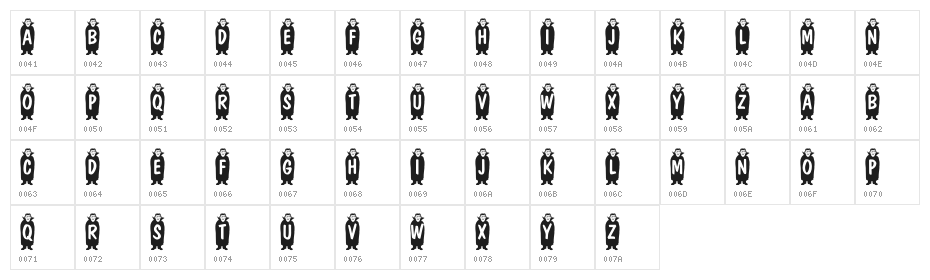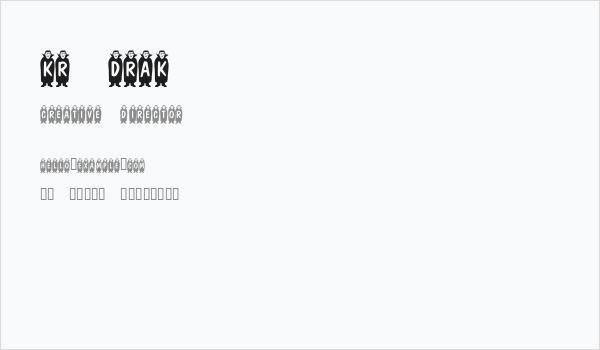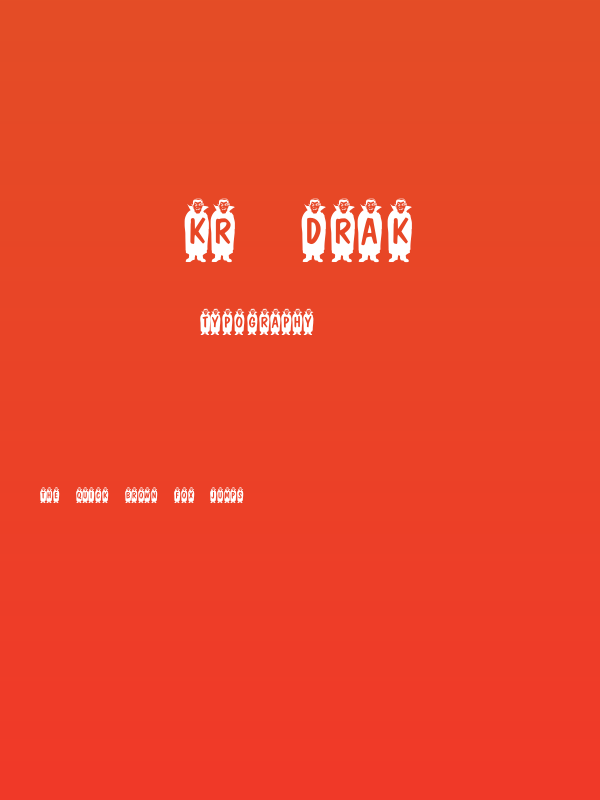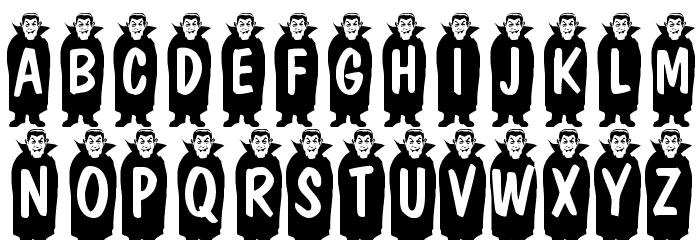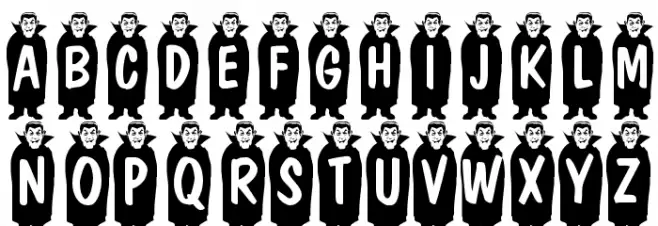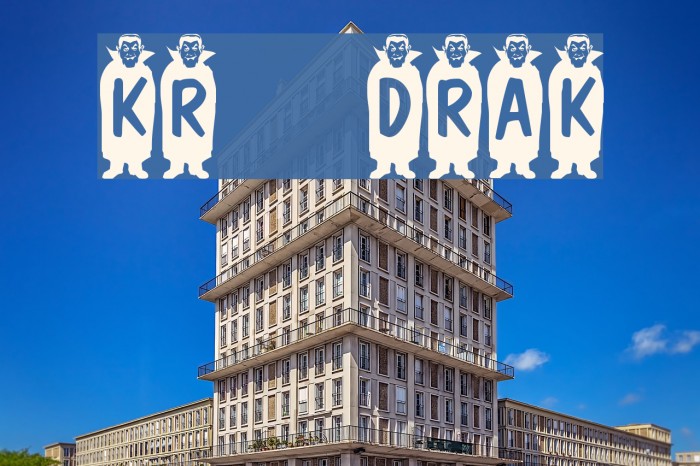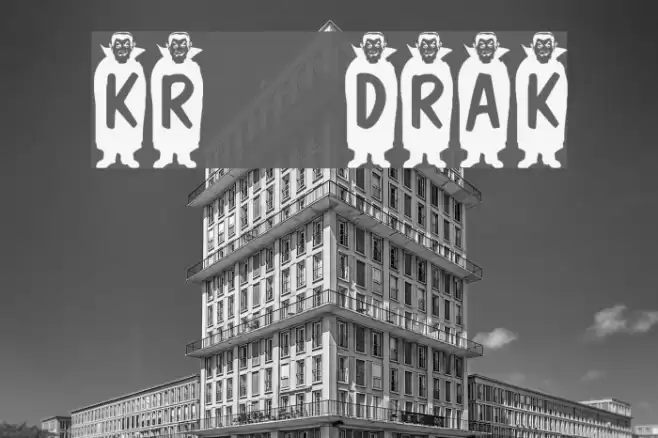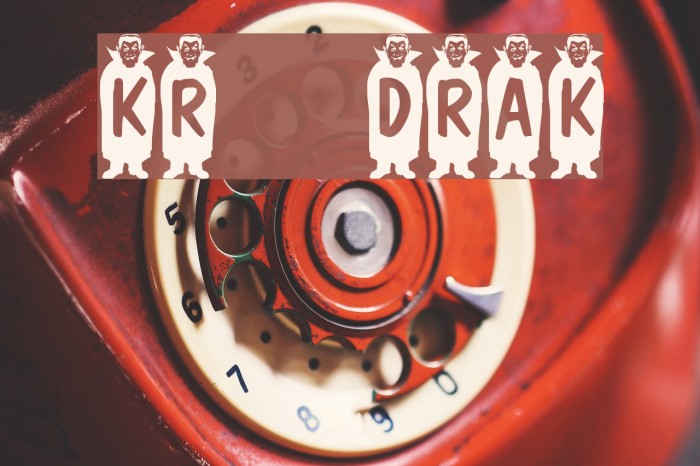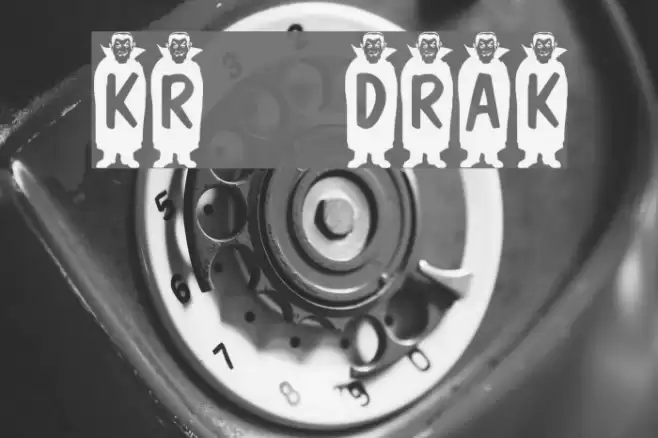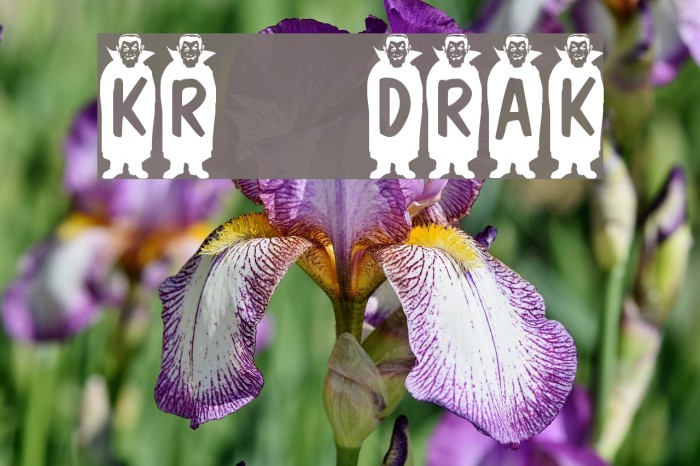
KR Drak Font
| Progetti proposti | Ideal for Halloween invitations, themed party decorations, children's books, or any project requiring a spooky, fun aesthetic. |